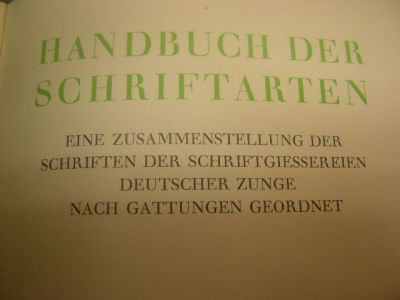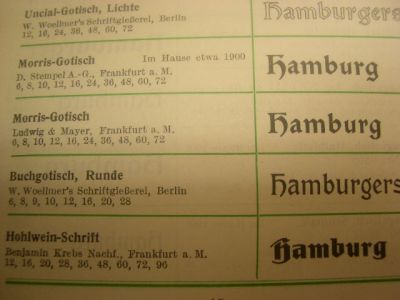
Welche Gebrochene Schrift ist das wohl?
kann mir bzw. uns alten Bleisetzern jemand sagen, um welche Gebrochene Schrift es sich hier handeln mag?
Ich dachte zunächst an eine Hamburger Druckschrift von Genzsch & Heyse. Aber die ist es nicht.
Im Laufe der Suche bekam ich den Eindruck, daß diese Schrift:
a) Nach 1926 entstand. Sie steht nicht im Seemann, der wohl umfangreichsten Hilfe für deutsche Bleisatz-Schriften vor 1926, dem Erscheinungsjahr des Buches.
b) Es sich eventuell gar nicht um eine deutsche Schrift handelt. Das E ist nicht typisch in der gezeigten Verbindung zum G und H.
c) Es sich vielleicht sogar - aber hier spekuliere ich nur, ohne Indizien anführen zu können - um eine modifizierte Schrift handelt, also eine Variante einer bestehenden, klassischen Schrift.
Hast Du da noch mehr zum Anschauen, vergleichen und suchen?
Daß Seeman sie nicht aufgeführt hat, muß nicht heißen, daß es sie nicht vor 1926 gegeben hat. Er schreibt ja, er hat nicht von allen Gießereien Schriftmuster bekommen.
Es gibt keine ähnliche, Schriftgießerei-übergreifende Sammlung von Bleisatz-Schriften aus dieser Zeit. Manchmal wünschte ich mir ein anderes Musterwort als immer nur "Hamburg". Aber gut, schon in Ordnung.
Ich nehme ihn jetzt meist für die Vorsuche und verifiziere das Ergebnis dann an der Hauptprobe der gefundenen Schriftgießerei. Die Koralle war die erste, die ich dort gefunden habe. In meiner Hauptprobe von Schelter & Giesecke von 1908 steht sie naturgemäß noch gar nicht drin.
Das ist der Seemann.
Ein Handbuch für Schriften. Die hat der Herr Seemann damals von allen existierenden Schriftgießereien, die wollten, eingesammelt - in Form des Wortes "Hamburg". Und dann hat er sie, sortiert nach Gattungen und versehen mit Informationen, gedruckt.
Es zeigt keinen vollständigen Zeichensatz. Und das Wort "Hamburg" verschafft einem nicht einmal eine ausreichende Anmutung für die Schrift. Aber für meine Arbeit, das Klassifizieren, ist er Gold wert.